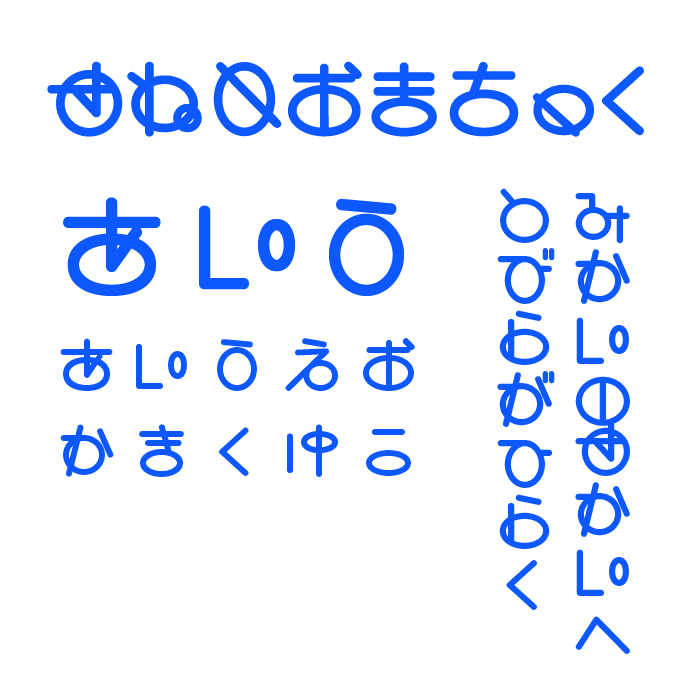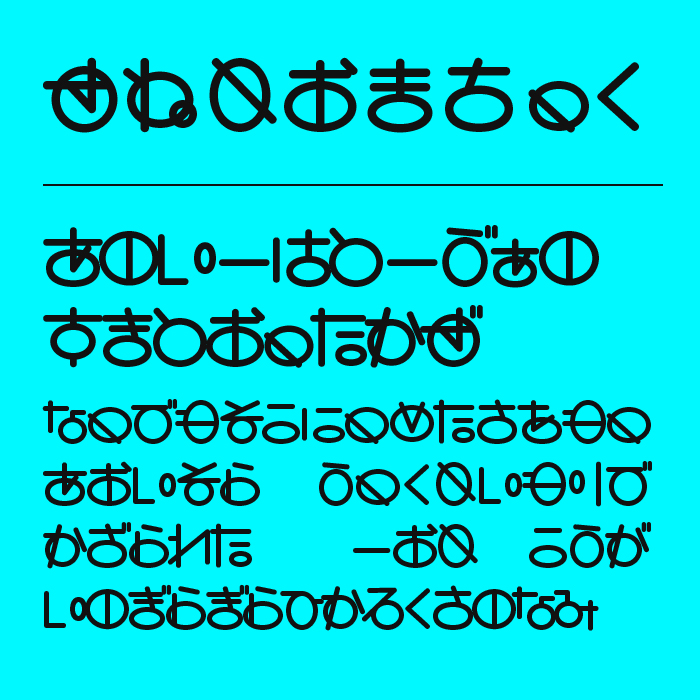
セネシオまちっくフォントは、幾何学的な抽象的で愛らしいグリフが並ぶ個性派デザインフォントです。
文字の形を極限までデフォルメしており、視認性を犠牲にしてでもインパクトを残す構造がユニーク、暗号や記号なデザインとなっているフォントです。
全体としては子ども向けの可愛らしさと、近未来的な実験性をあわせ持った、不思議で魅力的な雰囲気を演出します。装飾的な場面やビジュアルコンテンツで、強烈な個性を求めるときに活躍するフォントです。